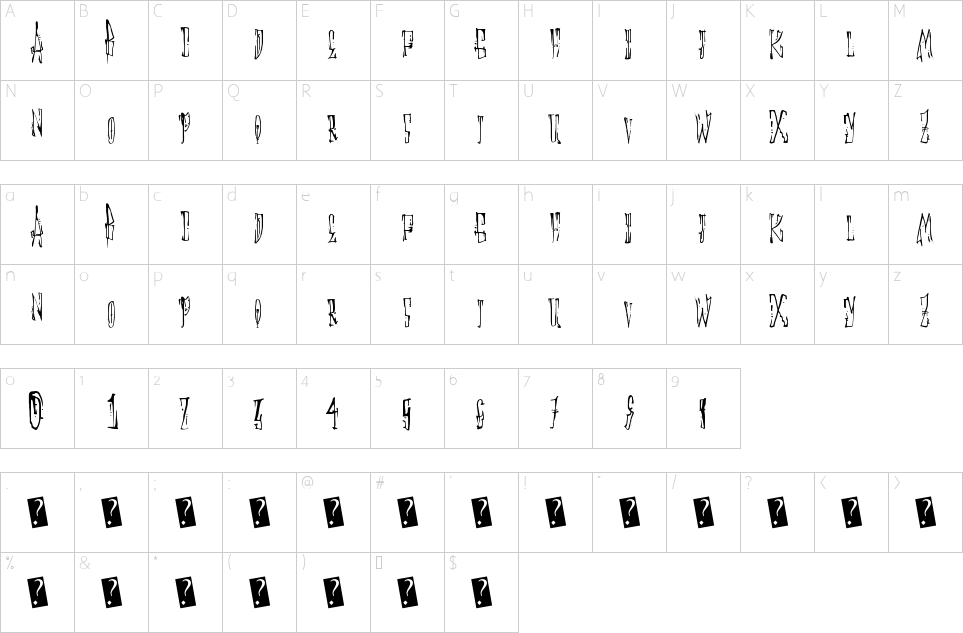
Descubra Animal Cracker, uma fonte de graça para Windows e Mac. Desenvolvida pelo designer desconhecido Xerographer Fonts, Animal Cracker oferece uma textura animada e divertida. Esta fonte foi projetada para aqueles que buscam uma mistura de leveza e simplicidade em seus projetos. Com sua aparência alegre e alegre, Animal Cracker é perfeita para uma gama de usos, desde materiais de marketing até ilustrações. Com seu design atraente e versátil, Animal Cracker é uma fonte que você vai querer ter na sua arsenal de recursos gráficos. Descubra agora e descubra por si mesmo o charme deste design único.